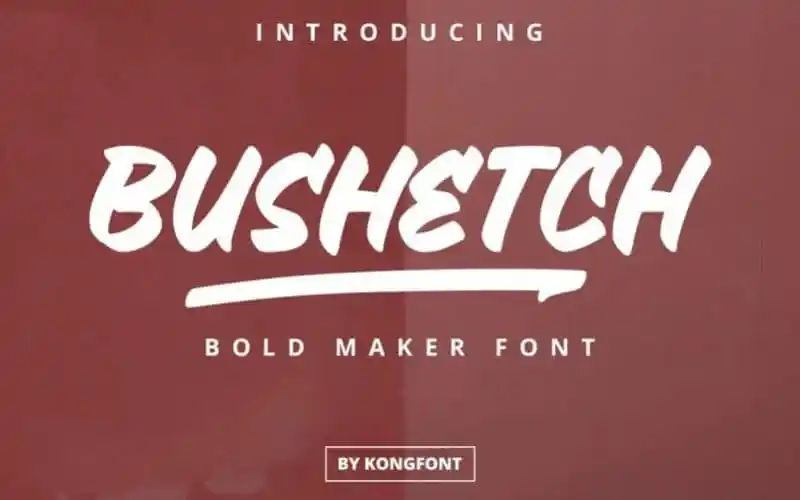
Bushetch Brush Font – Download Grátis
A Bushetch Brush Font surge diretamente das digitais humanas, combinando elegantes curvas com vibrações nostálgicas. Este conjunto de letras e números é perfeito para seus projetos, especialmente adequado para Logotipo, Design de Marca, Design de Logomarca, Arte de Letras Digitais, T-Shirts e Vestuário, Posters, Revistas, Sinalização, Design Publicitário, além de qualquer outro projeto que precise de uma identidade visual moderna e sofisticada. Seja você um designer ou um aficionado pela arte do design, esta fonte não deixará nada a desejar no mundo das letras digitais.